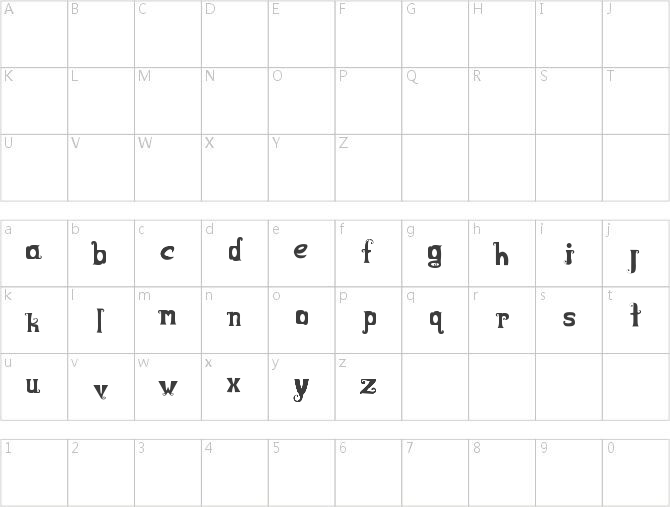
Boots-BarkleyRegular
Boots-BarkleyRegular介绍
Boots-BarkleyRegular字体字库是一款让人赏心悦目、百看不厌的英文字体,适合各类广告和产品包装设计应用,字体大小0.03MB,格式为ttf字体,上传用户是得·岸,作者/版权方为未知
Boots-BarkleyRegular效果图